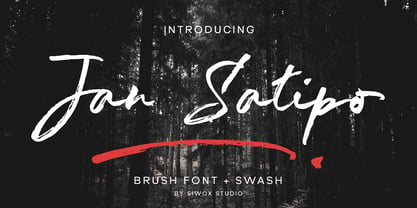
Jan Satipo Brush
by Siwox Studios
The Jan Satipo Brush Font Family was designed by Rizaldi Wandani and published by Siwox Studios. Jan Satipo Brush contains 1 styles. More about this family
Segarkan proyek desain Anda berikutnya dengan pesona spektakuler "Jan Satipo Brush Font". Font organik dan bersemangat ini dirancang untuk menghadirkan unsur estetika alam ke dalam karya kreatif Anda. Pilihan ideal untuk memperindah slogan, judul, sampul buku, dan logo, Jan Satipo Brush Font juga dapat memercikkan keajaibannya pada kutipan, undangan, dan poster keseharian Anda. Memberikan desain Anda daya tarik yang hijau, font ini juga menampilkan karakter alternatif yang khas dan goresan sapuan yang memikat yang pasti akan menarik perhatian. Biarkan desain Anda berbicara dalam bahasa alam dengan Jan Satipo Brush Font!
Designers: Rizaldi Wandani
Foundry: Siwox Studios